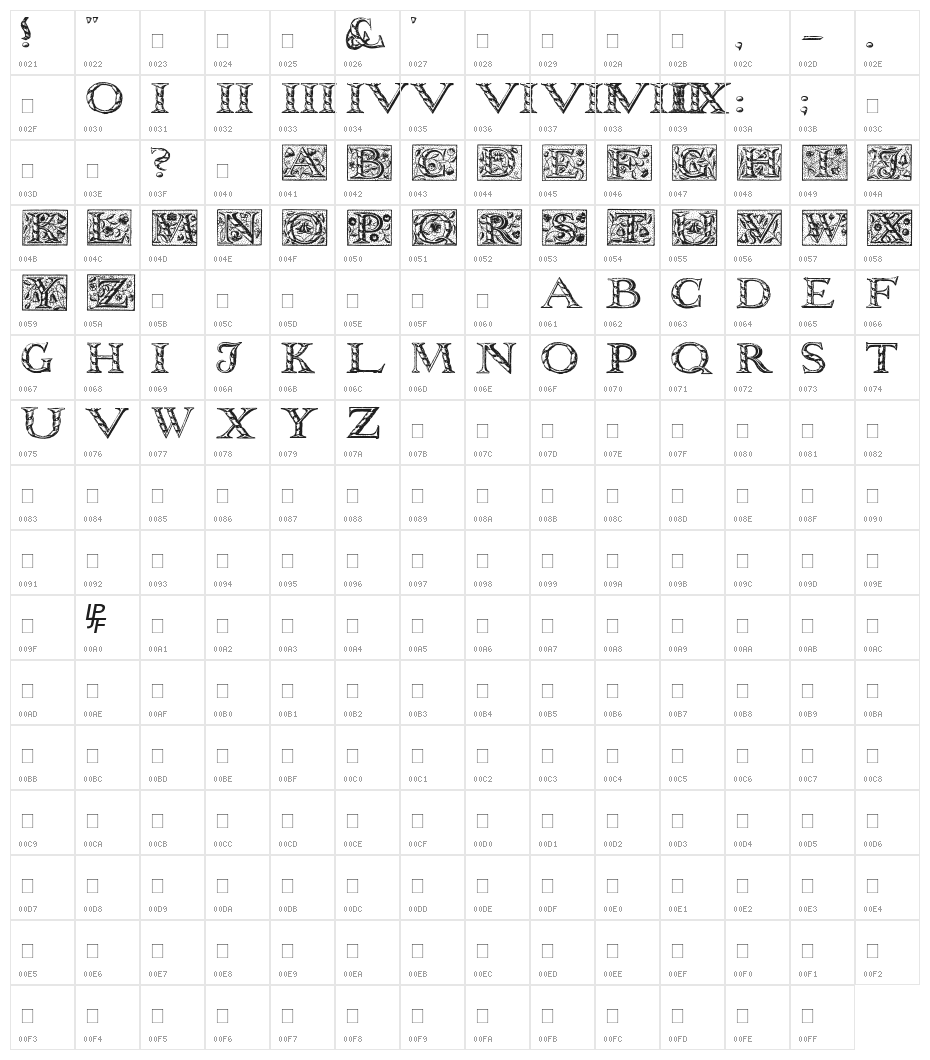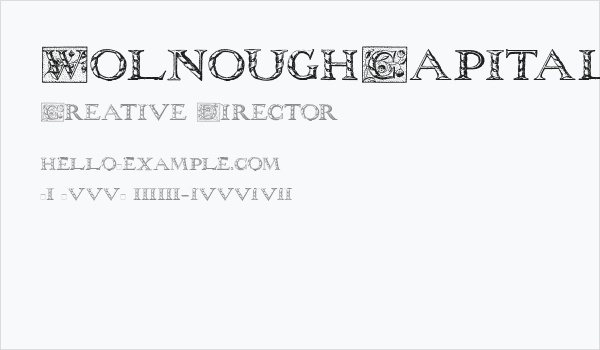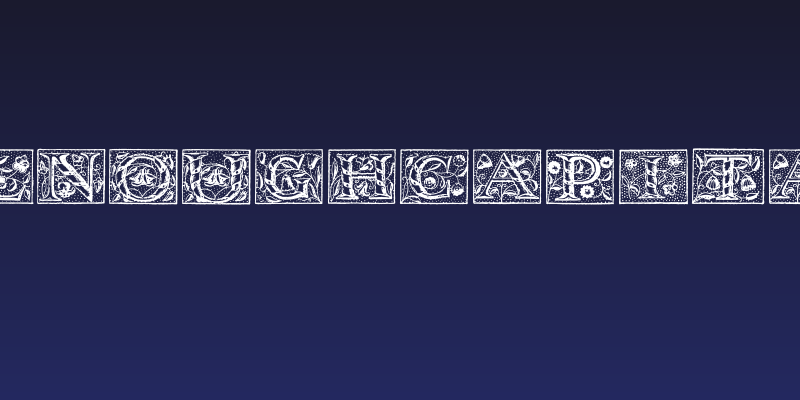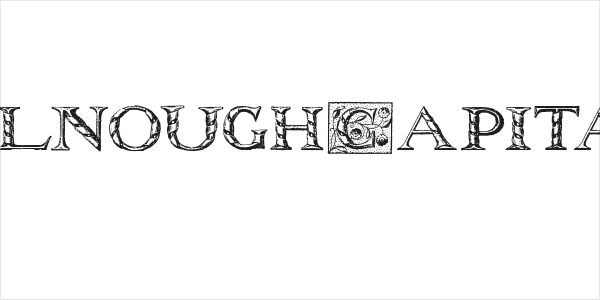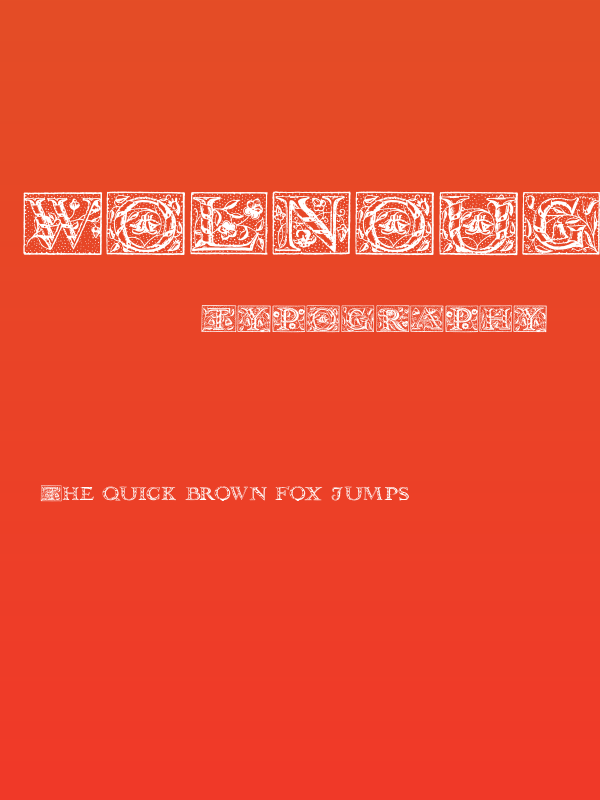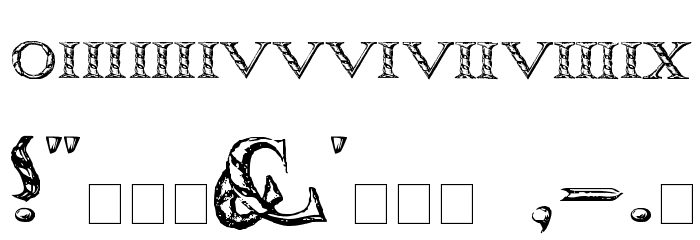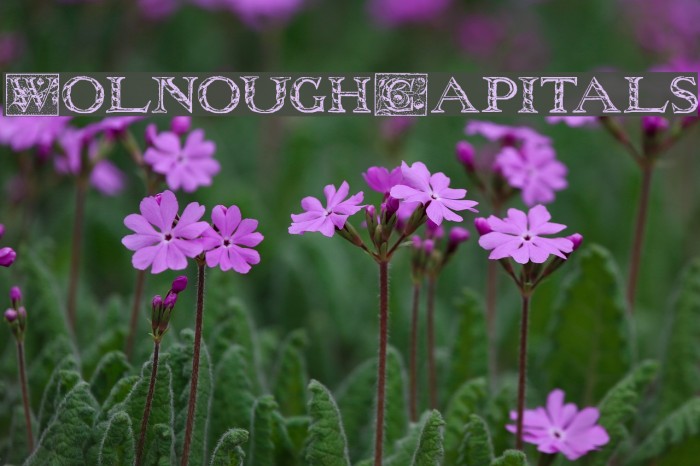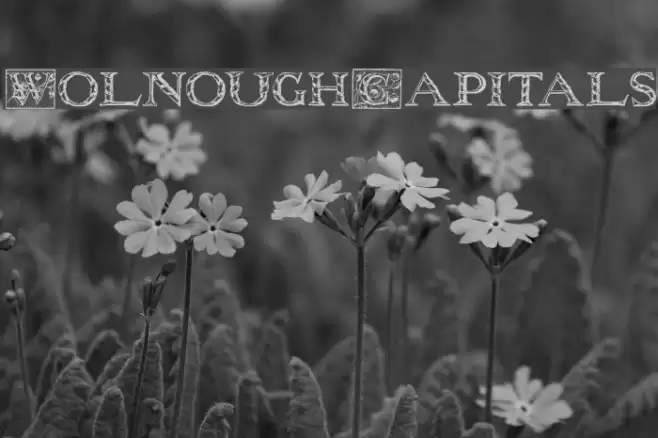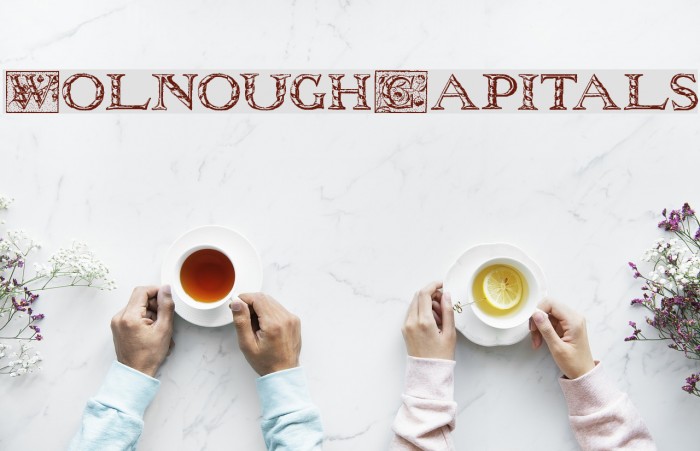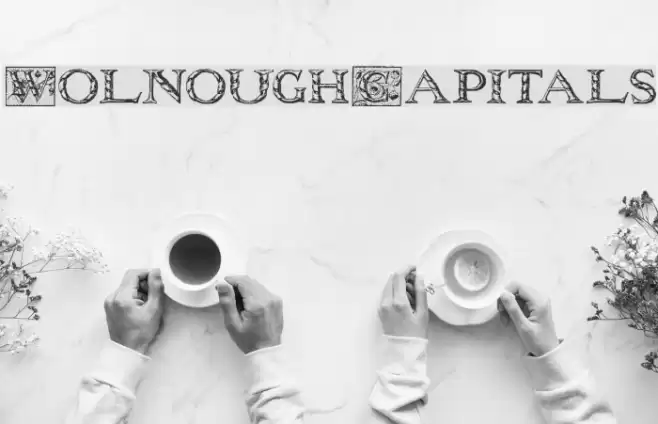
WolnoughCapitals Font
| Projets proposés | Ideal for use in historical-themed projects, book covers, invitations, or branding that requires a classic and sophisticated touch. |